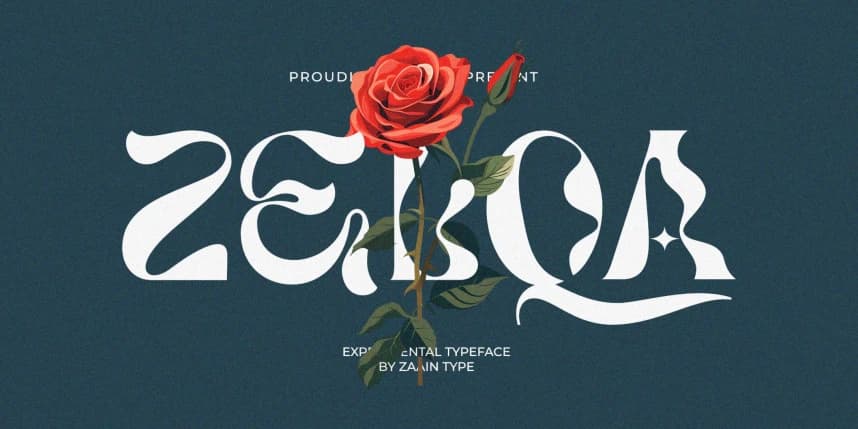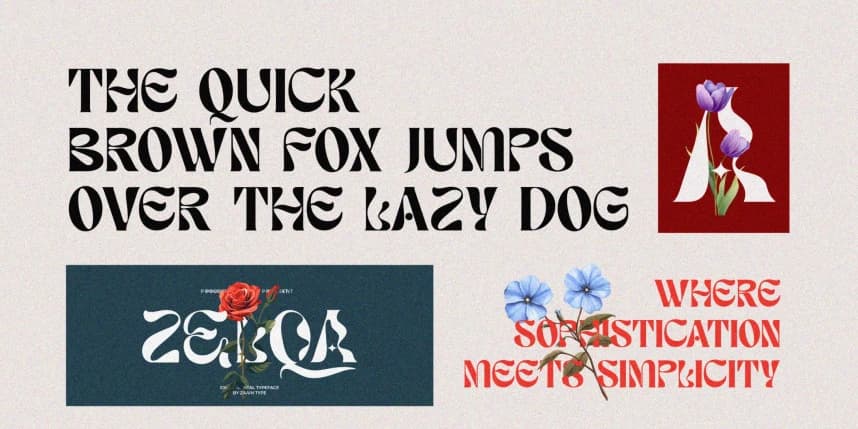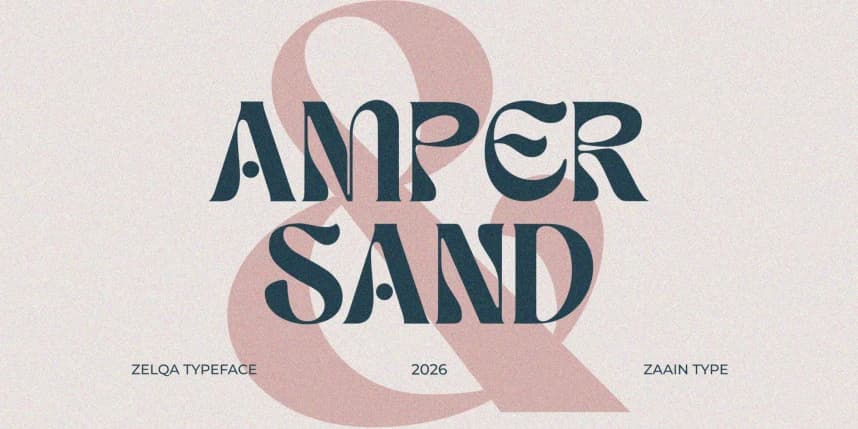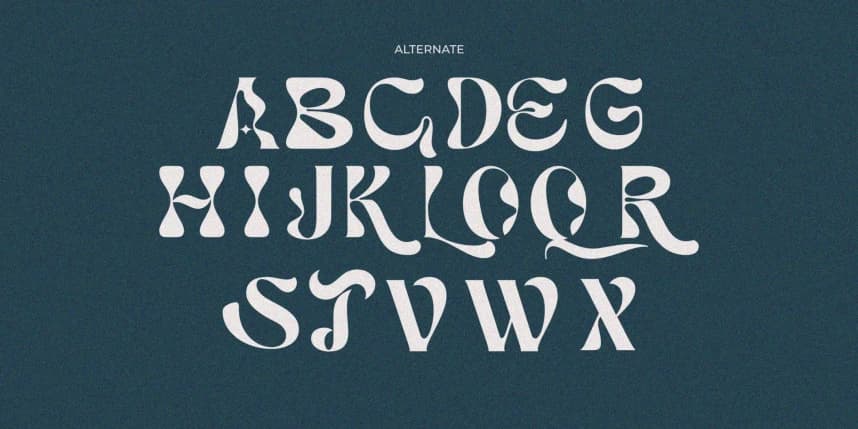
Zelqa Font
Zelqa Font, geleneksel tasarımın sınırlarını zorlayan deneysel bir tipografidir. Alışılmadık şekilleri, dinamik kontrastları ve beklenmedik harf tasarımlarıyla Zelqa, modern yaratıcı projelerde öne çıkan cesur bir görsel ifade sunar.
Zelqa Font, geleneksel tasarımın sınırlarını zorlayan deneysel bir yazı tipidir. Alışılmadık biçimleri, dinamik karşıtlıkları ve beklenmedik harf biçimleriyle Zelqa, modern yaratıcı projelerde öne çıkan cesur bir görsel ifade sunar.